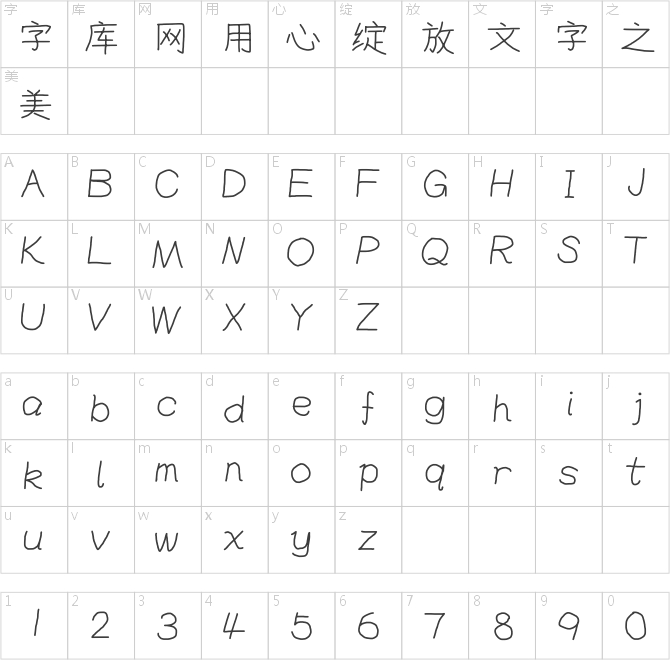
字体名称: 快去写作业CJ
快去写作业CJK
快去写作业CJK是B站UP主@派对大魔王制作的一款免费商用手写字体。
快去写作业CJK字体CEF Fonts CJK字库是一款让人赏心悦目、百看不厌的中文字体,适合各类广告和产品包装设计应用,字体大小24.7MB,格式为ttf字体,上传用户是猫七,作者/版权方为派对大魔王